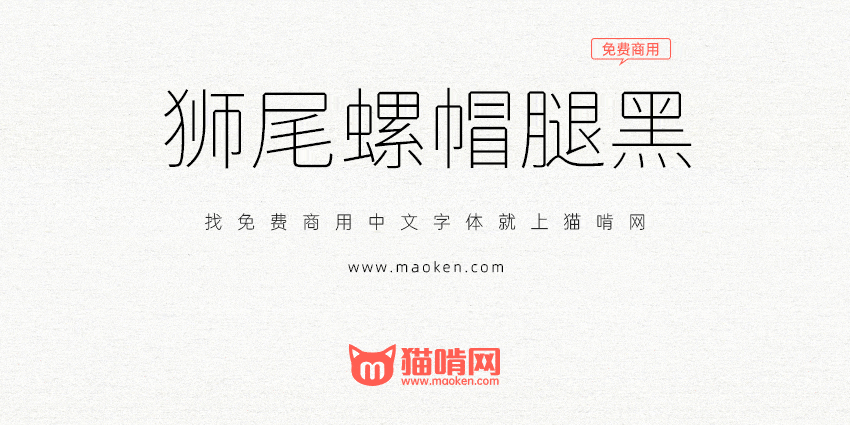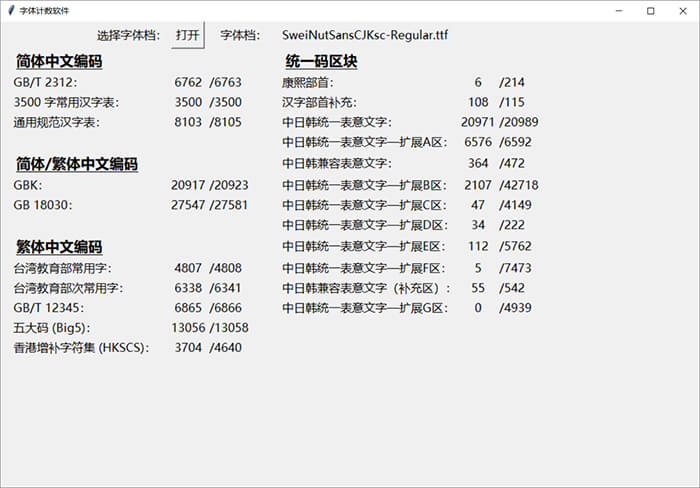
狮尾螺帽腿黑体基于思源黑体增加斜角和拔脚改造,更加简明现代化的字体。支援简体中文、繁体中文、韩文与日文;欢迎大家自由应用、自由优化、自由改作!
狮尾螺帽腿黑体的特色是,“口”字的转角处增加一个斜角,外形有点像螺帽。
狮尾螺帽腿黑体和狮尾螺帽腿黑体差别在有没有拔脚,“拔脚”就是会有较少的笔画,例如移除“口”字的左右下角会多出的短线条。有拔脚的字会较圆,但是会造成有些字因直接去掉腿后左右不平衡、左右不对称的“悬空”问题。改使用“腿”系列字体就不会有这个问题。